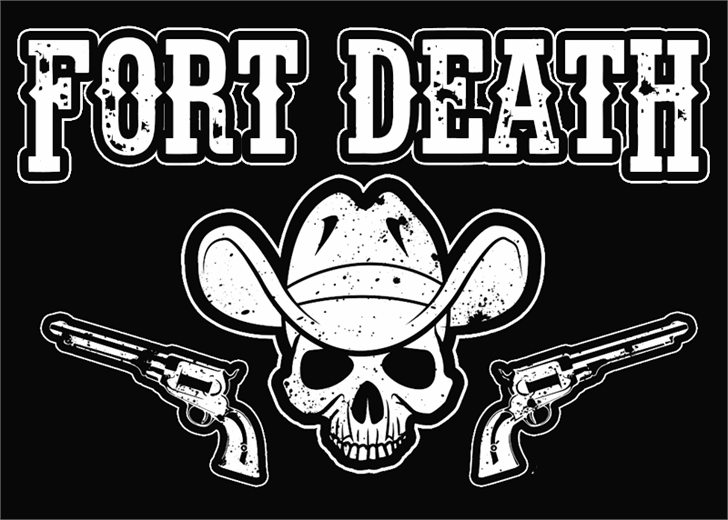
A fonte Fort Death é uma escolha perfeita para criadores de designs que procuram algo único e instigante para seus projetos. Embora tenha sido desenvolvida como um tipo gothic, a Fort Death oferece uma combinação única de numeral, itálico e versão sólida em sua versão licenciada, garantindo diversidade nos seus trabalhos. Hamilton é o designer responsável por essa fonte marcante. Os recursos informativos sobre seu uso estão disponíveis no site Fontmonger e na pagina da Crisvile. Com uma tipografia tanto delicada quanto poderosa, a Fort Death adere ao estilo do gothic enquanto oferece uma perspectiva única que certamente chamará a atenção. Para criadores de design digital ou impressão, esta fonte é uma excelente opção para introduzir um toque diferente e interessante em suas obras. Combinar os elementos numeral, itálico e sólido permite um amplo leque de possibilidades no seu projeto gráfico, tornando a Fort Death uma fonte que merece estar na sua coleção.